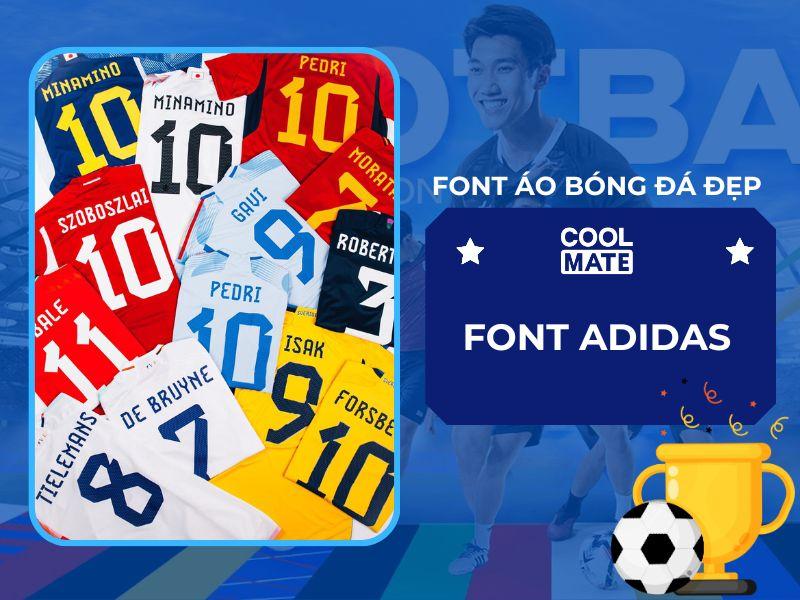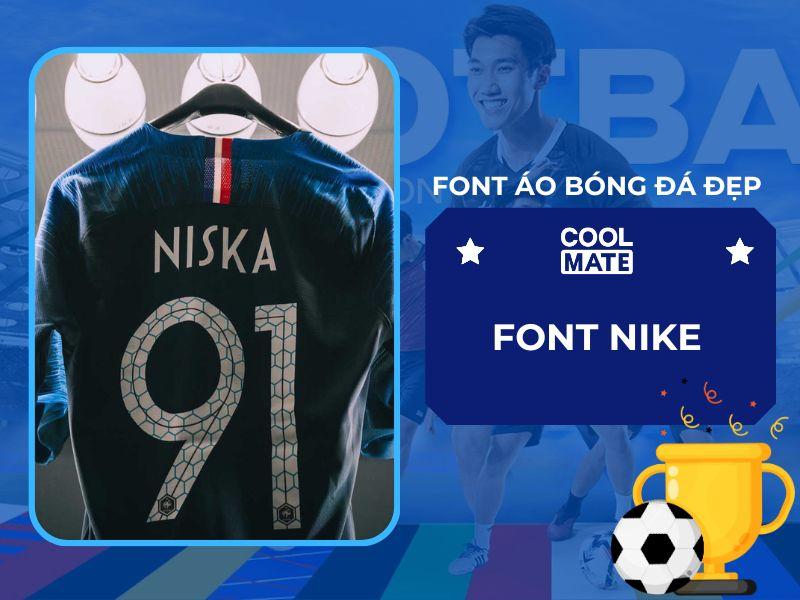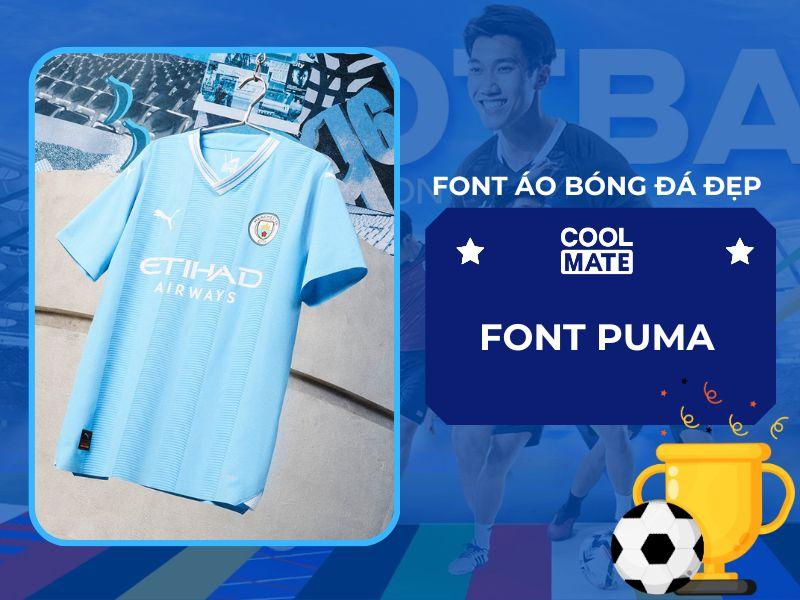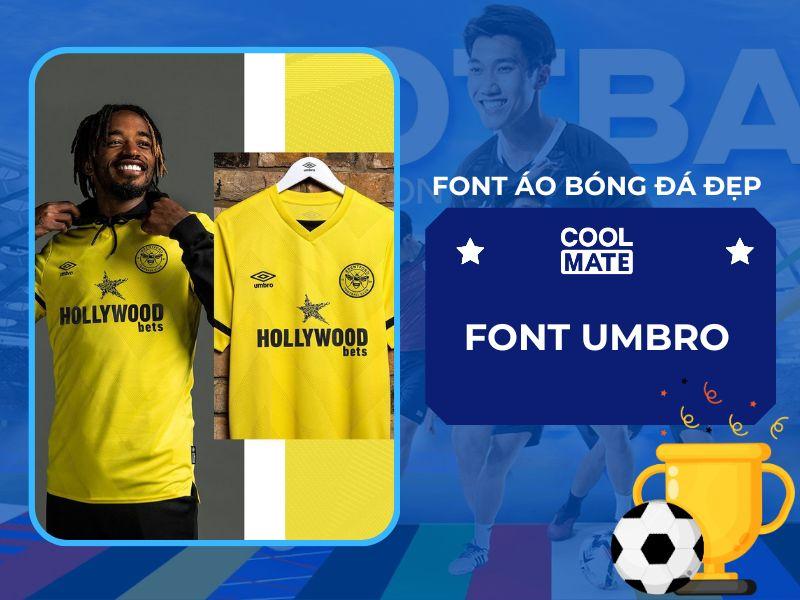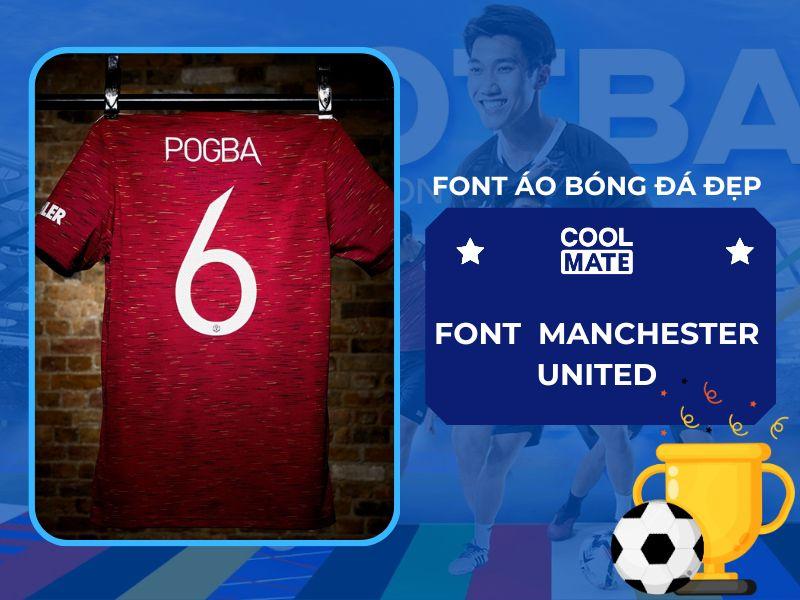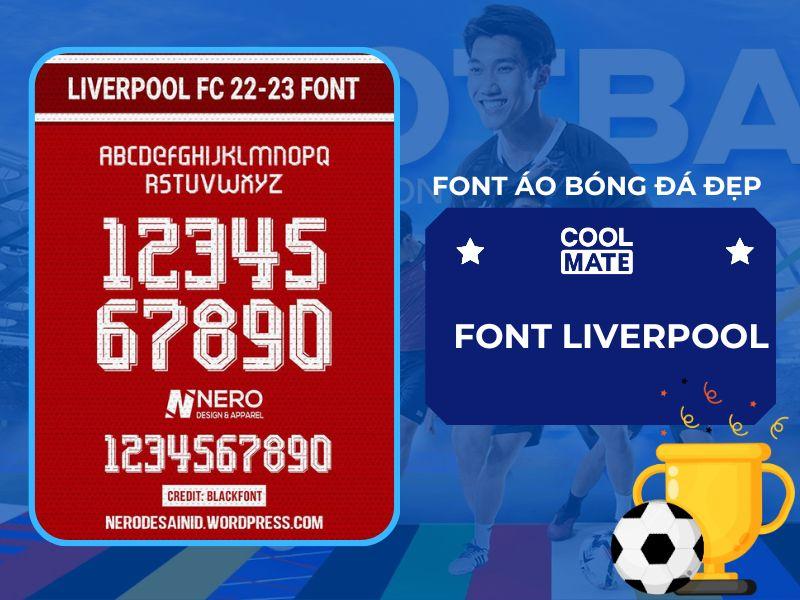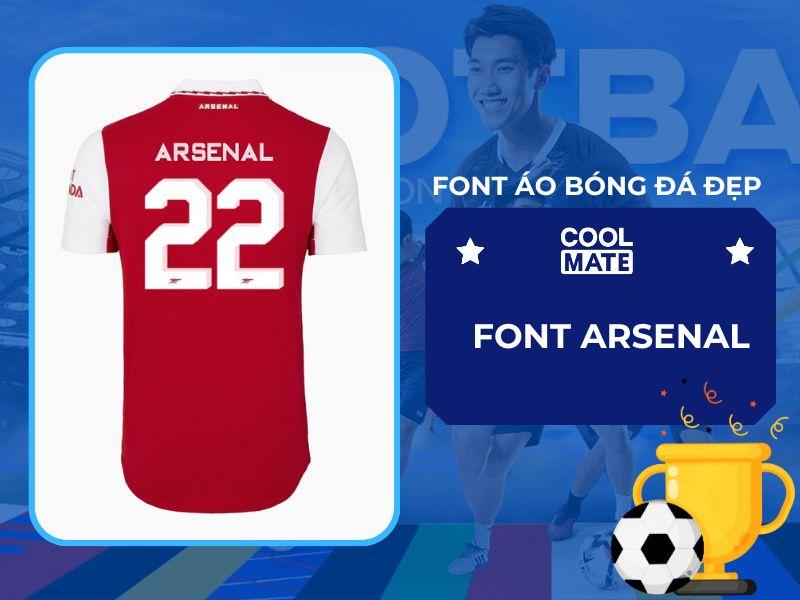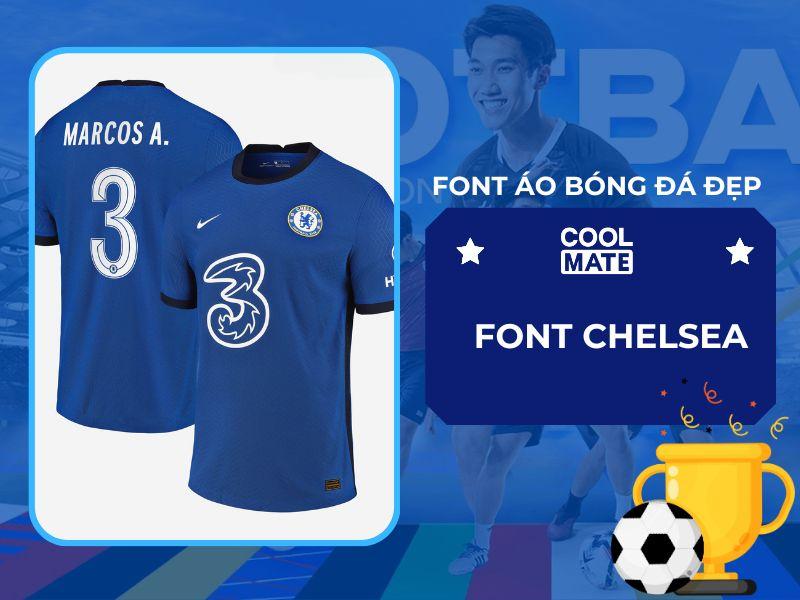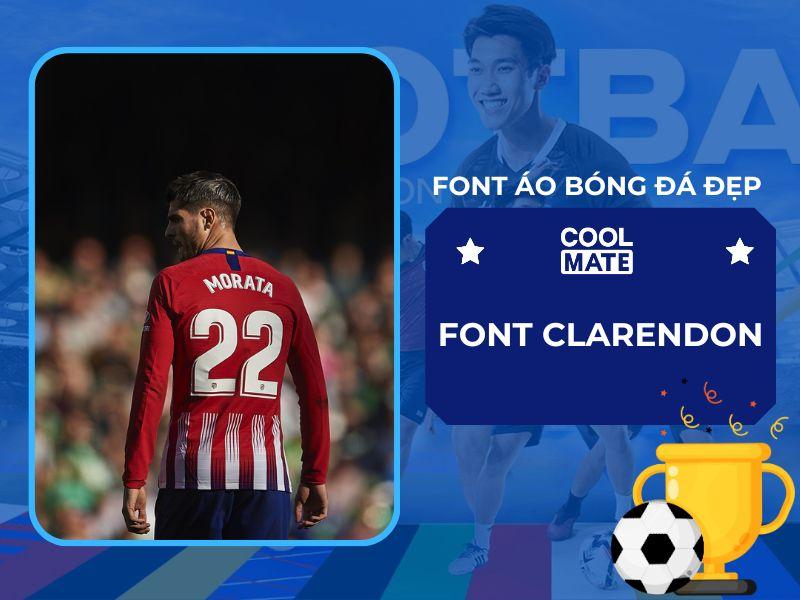
Trong bóng đá, áo đấu không chỉ là bộ trang phục để nhận biết đội bóng mà còn là biểu tượng của tinh thần đoàn kết và sự chuyên nghiệp của đội. Trong đó, font chữ in áo bóng đá đóng vai trò vô cùng quan trọng. Để hiểu rõ hơn về khái niệm và lợi ích của font chữ in lên áo bóng đá, hãy cùng Coolmate tìm hiểu qua bài viết này.
Tổng quan về font chữ in áo bóng đá
Font chữ in lên áo bóng đá là việc sử dụng kiểu chữ đặc biệt để in tên và số áo của cầu thủ lên bộ đồ đấu. Có nhiều loại font chữ khác nhau và mỗi đội bóng đều có thể sử dụng font chữ riêng để tạo nên sự độc đáo và riêng biệt cho đội nhà.
Font chữ áo bóng đá tạo điểm nhấn riêng cho từng đội bóng
Việc lựa chọn font chữ phù hợp cũng quan trọng không kém việc chọn thiết kế cho một chiếc áo in hình ấn tượng.
Tổng hợp các font chữ in áo bóng đá đẹp và phổ biến hiện nay
1. Font chữ Adidas
Đứng đầu trong danh sách các mẫu chữ in áo thể thao đó chính là font chữ Adidas. Với kiểu chữ độc đáo, mạnh mẽ và thể thao, font chữ Adidas đã trở thành biểu tượng của thương hiệu thể thao hàng đầu này.
Được sử dụng trên các sản phẩm của Adidas từ giày, quần áo, túi xách và đặc biệt là áo bóng đá, font chữ Adidas mang lại sự phong cách và độc đáo cho những sản phẩm này. Với những dòng chữ sắc nét, đậm và các đường nét được thiết kế tỉ mỉ, font chữ Adidas cũng thể hiện sự mạnh mẽ, sự nhanh nhẹn và đầy quyết đoán.
Font chữ Adidas là một kiểu chữ thể thao mạnh mẽ, với các đường nét đơn giản
Ngoài ra, font chữ Adidas còn có khả năng tùy chỉnh linh hoạt để phù hợp với nhiều kiểu áo bóng đá khác nhau. Thật dễ dàng để sử dụng font chữ này để in lên các loại áo bóng đá khác nhau với những màu sắc và kiểu dáng. Với sự phổ biến của thương hiệu Adidas và font chữ này, không có gì ngạc nhiên khi thấy nhiều đội bóng đá lớn trên toàn thế giới sử dụng font chữ Adidas để in lên áo của họ. Những đội bóng như Real Madrid, Manchester United, Bayern Munich và Paris Saint-Germain đều đã sử dụng font chữ Adidas để tạo ra những bộ áo đẹp mắt và phong cách.
2. Font chữ Nike
Font chữ Nike là một trong những font chữ phổ biến và đẹp hiện nay. Nó được sử dụng phổ biến trong thiết kế áo bóng đá và trở thành biểu tượng của thương hiệu Nike. Với thiết kế đơn giản, mạnh mẽ và năng động, font chữ Nike mang đến một cảm giác hiện đại và chuyên nghiệp cho các đội bóng. Với phông chữ đậm và những đường nét đơn giản, font chữ này rất dễ đọc và phù hợp cho việc in lên áo bóng đá.
Một điều đặc biệt về font chữ Nike là nó có thể được sử dụng cho nhiều mục đích khác nhau. Nó không chỉ được sử dụng cho thiết kế áo bóng đá, mà còn được sử dụng trong thiết kế logo, banner, và các ấn phẩm quảng cáo khác. Nếu bạn đang tìm kiếm một font chữ đẹp và phổ biến để in lên áo bóng đá của đội bóng mình, font chữ Nike là sự lựa chọn hoàn hảo. Với sự đơn giản, tinh tế và sức mạnh của nó, font chữ Nike sẽ giúp đội bóng của bạn nổi bật hơn trong mắt các fan hâm mộ và đối thủ.
Font chữ Nike là một kiểu chữ đậm nét, đơn giản và hiện đại
3. Font chữ Puma
Font chữ in áo bóng đá Puma mang đến cho người xem một cảm giác đầy mạnh mẽ và khỏe khoắn. Nó được thiết kế với những đường nét rõ ràng và đậm nét, tạo nên một phong cách thể thao đầy năng động. Đặc biệt, Puma còn có nhiều biến thể khác nhau, từ đơn giản cho đến phức tạp, giúp người thiết kế có thể dễ dàng tạo ra những mẫu áo bóng đá độc đáo và thú vị.
Font chữ Puma cũng được sử dụng rộng rãi trên các sản phẩm quần áo và giày thể thao của Puma. Điều này giúp thương hiệu này tạo nên một phong cách thời trang độc đáo và sành điệu, thu hút được đông đảo khách hàng yêu thích thể thao và thời trang.
Font chữ Puma là một kiểu chữ sans-serif đơn giản, hiện đại và dễ đọc
4. Font chữ Umbro
Font chữ Umbro là một trong những font chữ phổ biến và được ưa chuộng trong việc đồng phục thể thao. Được ra mắt từ năm 1924, Umbro đã từng là đối tác cung cấp thiết bị, phụ kiện thể thao cho các đội tuyển Anh, Brazil và Ireland. Hiện nay, Umbro được sử dụng rộng rãi bởi các đội bóng lớn trên thế giới như Brentford, Everton và West Ham United,…
Font chữ Umbro là một kiểu chữ sans-serif gọn gàng và hiện đại
Font chữ Umbro có nét chữ mạnh mẽ, sắc nét và độc đáo, khiến cho áo bóng đá trở nên thật sự đặc biệt và cá tính. Đặc biệt, nét chữ này có thể dễ dàng được phân biệt và nhận ra, đó cũng là lý do tại sao nó được sử dụng phổ biến trên các sản phẩm in áo bóng đá. Với việc sử dụng font chữ Umbro, các đội bóng có thể tùy chỉnh và thiết kế áo bóng đá theo phong cách của mình, tạo ra một sản phẩm độc đáo và phong cách riêng cho từng đội bóng.
Đồng thời, với sự phát triển của công nghệ in ấn hiện đại, các đội bóng có thể in font chữ Umbro lên áo bóng đá của mình một cách dễ dàng và nhanh chóng.
5. Font chữ Manchester United
Nhắc đến những “con quái vật” trên sân cổ thì chắc chắn không thể thiếu clb thành công tại Anh Quốc – “Quỷ đỏ” Manchester United. Là một trong những clb có lịch sử hoạt động lâu đời (1878), trong suốt hành trình trinh phục các giải đấu, đội bóng đã sử dụng nhiều font chữ khác nhau để làn nổi bật mẫu áo đồng phục mang tính biểu tượng của mình.